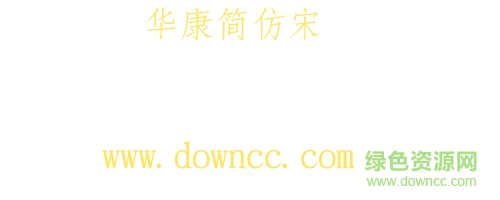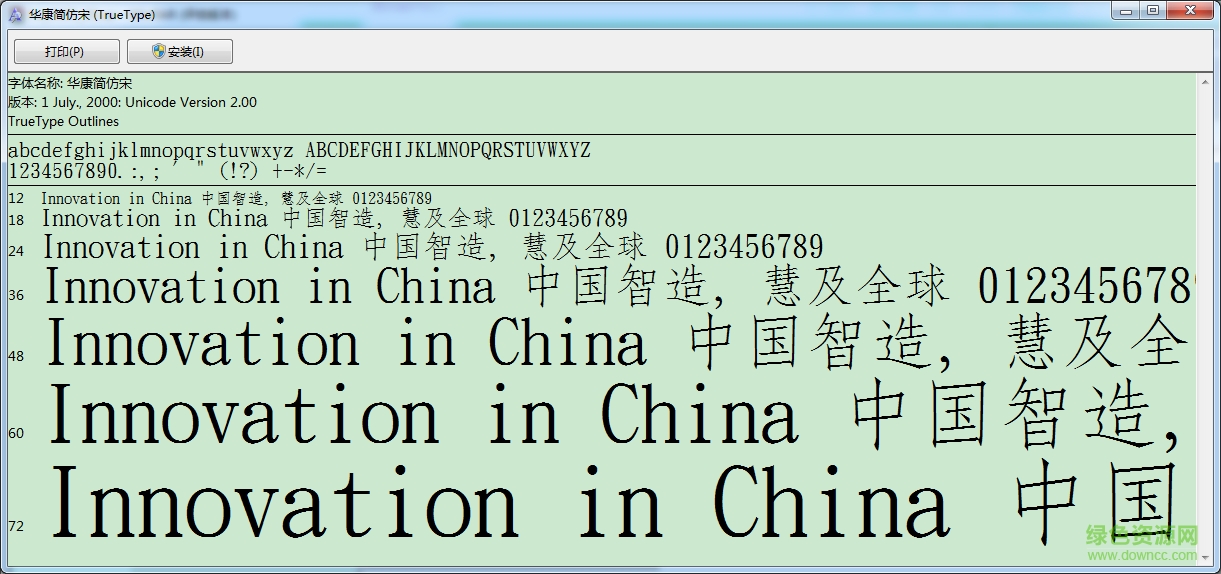
華康簡仿宋是一款非常漂亮的仿宋字體,這款字體筆畫清秀,字形比較端正大方,字形優(yōu)美,適用于廣告、美工、海報(bào)等,喜歡的朋友可以來綠色資源網(wǎng)下載免費(fèi)使用喲!
華康簡仿宋是一款非常標(biāo)準(zhǔn)的中文簡體漢字,該字體清秀纖細(xì),效果出眾,且結(jié)構(gòu)清晰、風(fēng)格統(tǒng)一,可應(yīng)用于正文標(biāo)題、印刷包裝、平面設(shè)計(jì)、辦公學(xué)習(xí)、繪畫創(chuàng)作等領(lǐng)域,喜歡的朋友可免費(fèi)下載收藏。